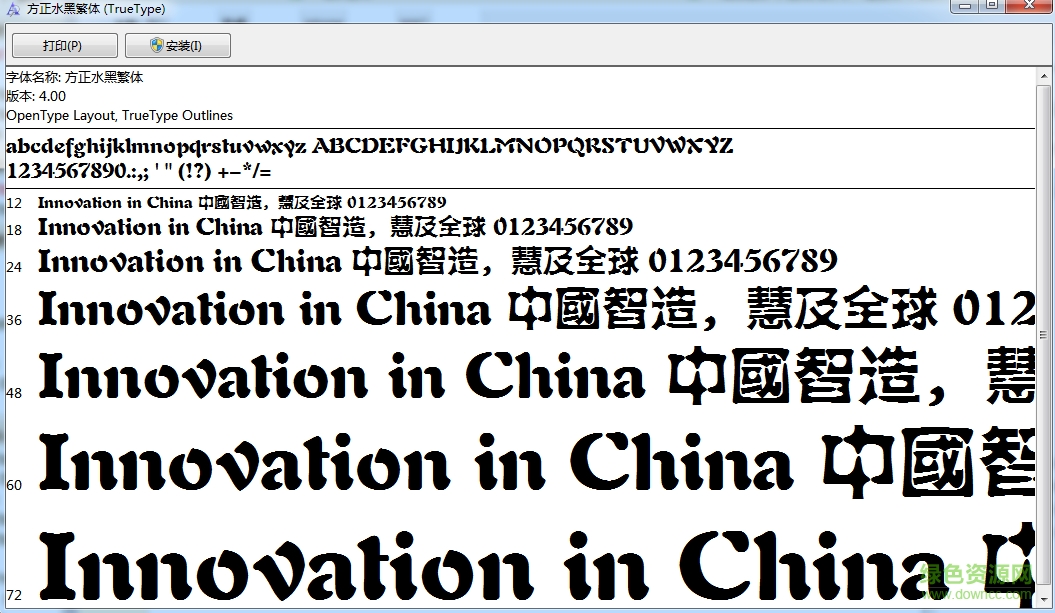
fzshhfw gb1 0字体是一款非常时尚的字体哦,这款字体是方正字体中的一款,也叫方正水黑繁体哦,有需要的朋友就来绿色资源网下载体验吧!
fzshhfw字体就是方正水黑繁字体,字形粗狂而又工整,水滴效果漂亮。该字体适用领域十分广泛,现绿色资源网提供fzshhfwgb10字体下载,有需要的就来吧!